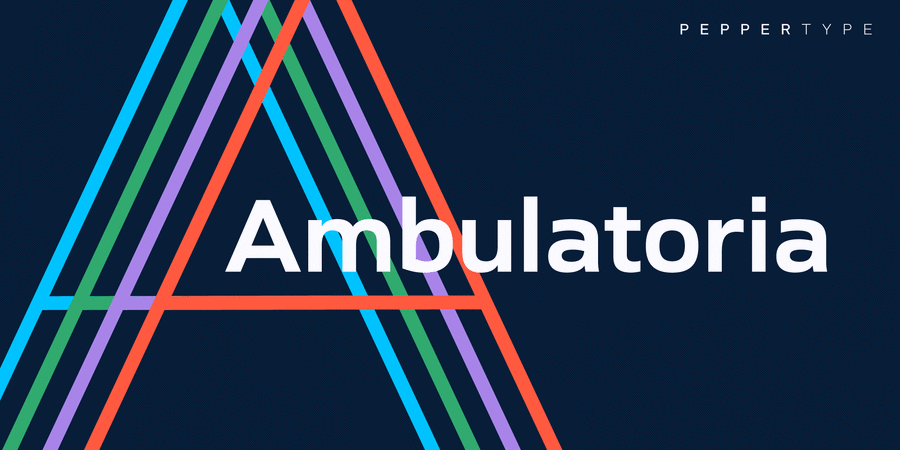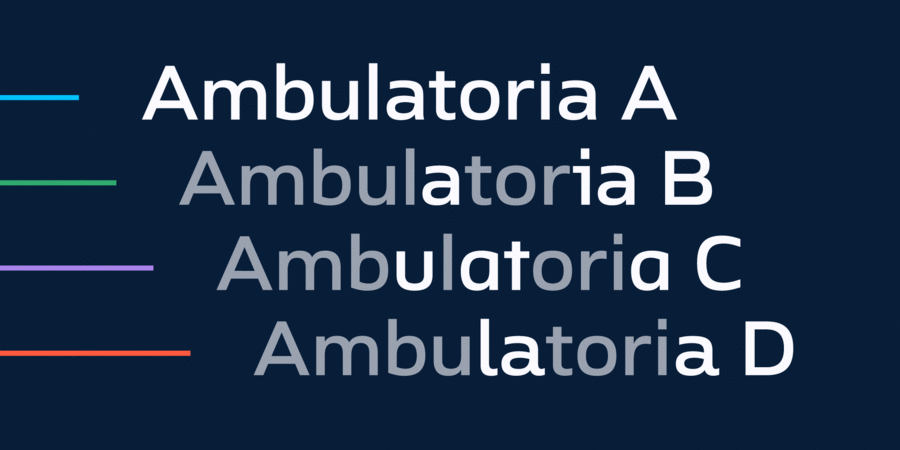
Ambulatoria C – третій із чотирьох наборів супергарнітури.
Ambulatoria – це міцний шрифт без засічок із відкритою апертурою, представлений у чотирьох варіантах. Кожен варіант: A, B, C і D містить альтернативні варіанти для певних гліфів, які дозволяють дизайнеру змінювати характер і текстуру шпальти.
Ця супергарнітура містить 80 накреслень, кожне з яких має багату мовну підтримку, включно з загальноєвропейською латинкою та кирилицею. Шрифт призначений для роботи з текстами як великого, так і маленького розміру, що робить Ambulatoria універсальною робочою конячкою.
Шрифт розробив Олег Ліщук у 2022 році.
Асоціації з сімейством шрифтів Ambulatoria CОсобистість і характер гарнітури:
мінімалістичний, делікатний, чистий, легкий, прохолодний, модний, тонкий, сучасний, рівний, якісний, невагомий, скляний, гострий, прозорий, інтимний, крихкий, дротяний, лаконічний, спокійний, свіжий, ясний, чіткий, логічний, точний, худий, доступний, комфортний, Простий, глобалізований, глобалістічний, міський, формальний, зрозумілий, технічний, гладенький, зручний, серйозний, непомітний, солідний, довірчий, впевнений, стійкий, переконливий, мотивуючий, сильний, важкий, потужний, помітний, яскравий, активний, амбітний, значний, міцний, мужній, кондовий, суворий, добротний, щільний, монументальний, гучний, сміливий, брутальний, надійний, індустріальний, техногенний, урбаністичний, авторитетний, важливий, діловий, крутий, залізничний, самостійний, відповідальний, західний, обов'язковий, швидкий, рішучий, спортивний, твердий, тісний, чорний
туалетна вода, інновації, перукарня, дієта, гігієна, чистота, парфумерія, лосьйон, шампунь, дизайн, прилад, суспільство, Місто, коворкінг, технології, медицина, техніка, наука, хімія, фізика, транспорт, навігація, комп'ютерна гра, бізнес, аеропорт, аптека, метро, ліки, автобус, автомобіль, авто, торгівля, магазин, реклама, інструмент, будівництво, ремонт, машинобудування, завод, промисловість, верстат, тренажери, сейф, екскаватор, металургія, вантажоперевезення, порт, вантажівка, далекобійник, двигун, урбаністика, електростанція, енергетика, мотор, прес, вагон, залізниця, паливо, спорт, Доставка, логістика, кіно Гарнітура має ознаки стилів: